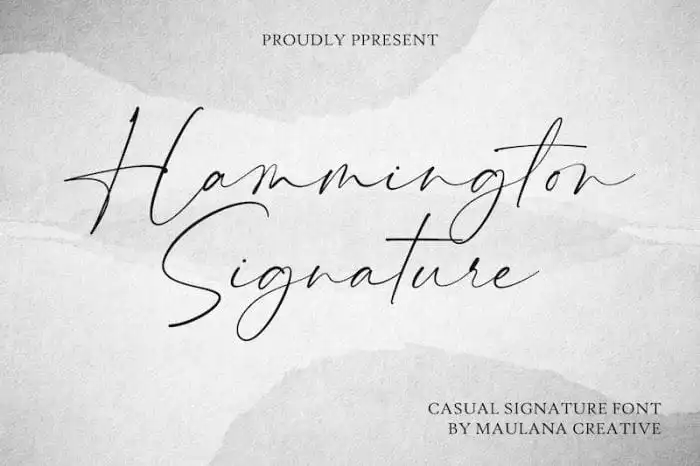
Hammington Script Font – Download Grátis
A Hammington Script Font é uma delicada e divertida escolha para designers que desejam dar um toque único a seus projetos visuais. Com suas letras cuidadosamente moldadas, ela cria texturas perfeitamente adequadas para assinaturas, cartelas de estação, logotipos, citações tipográficas, capas de revistas e livros, cabeçalhos de sites, roupas de marca, embalagens e mais. Suave em seu tom infantil e cheio de vida, ela também apresenta um toque adulto através do design inteligente, tornando-a uma escolha perfeita para qualquer projeto que deseje incorporar elementos únicos e atraentes.